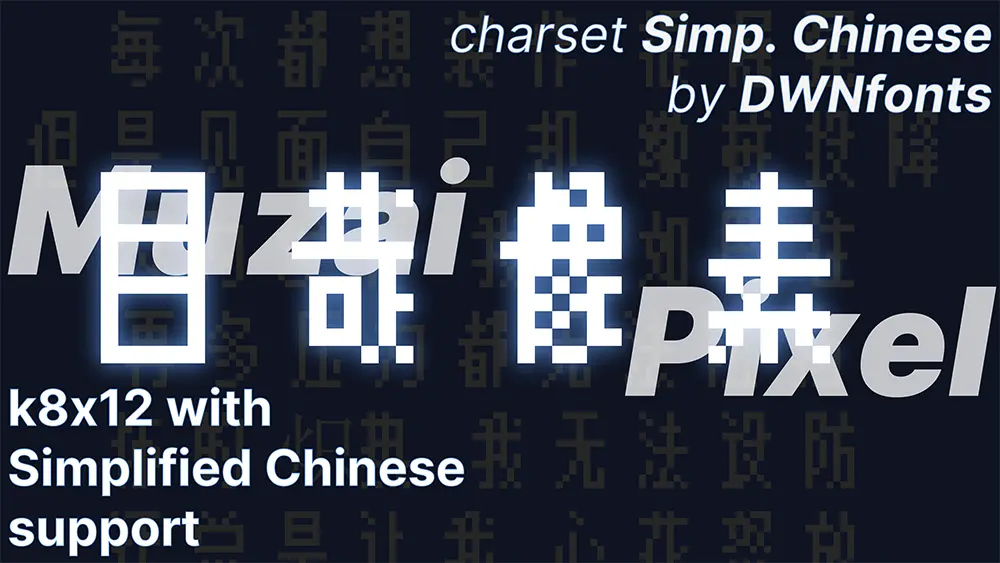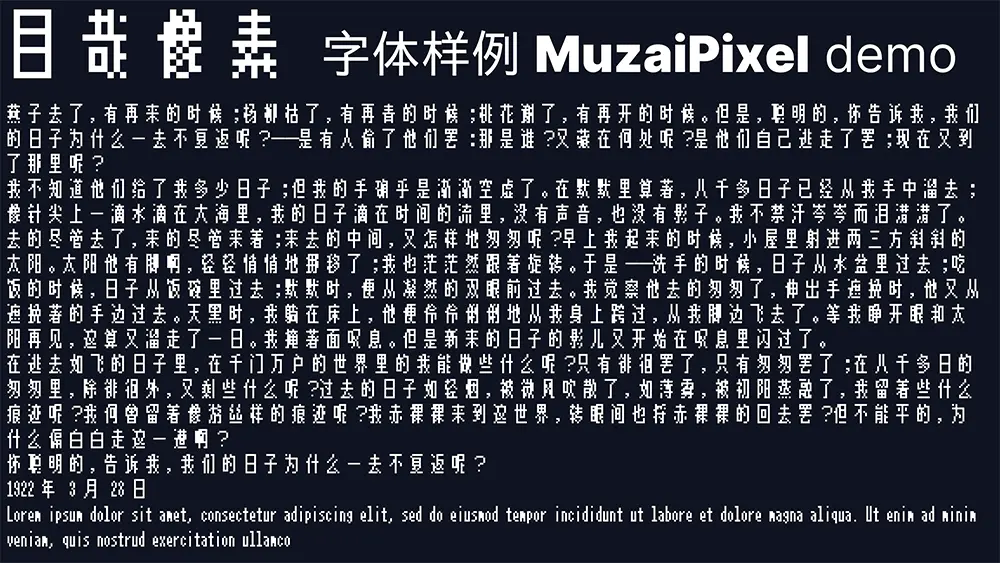
目哉像素 MuzaiPixel介紹
目哉像素(曾用名 k8x12j)是一個基於 k8x12 的 8x12 中日文點陣(像素)字體,這個字體的漢字覆蓋率可能不盡人意,會出現缺字。
為甚麼有倆字體?
original 版本像素是方的,如果你的工具沒有 bug 的話建議用這個
flat 版本拉寬到原來的 1.5 倍,如果你的工具有 bug,那就用這個,然後壓縮一下。